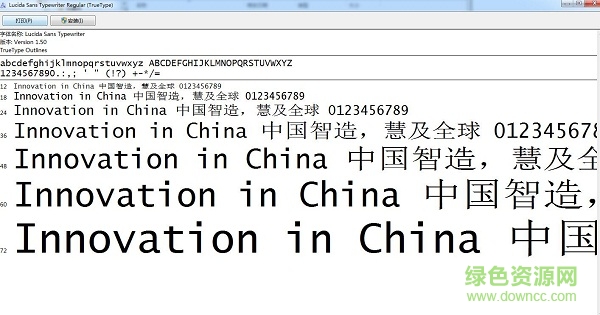
lucida sans typewriter字體是一款擁有高辨識(shí)性的經(jīng)典等寬字體,字型干凈大氣,易讀性出色,就像是打字機(jī)打出來(lái)的字體一樣,可用于網(wǎng)頁(yè)設(shè)計(jì)或編程設(shè)計(jì),歡迎大家免費(fèi)下載!
【Courier】
是一個(gè)等寬字體的粗襯線字體,主要是依據(jù)打字機(jī)所打印出來(lái)的字形來(lái)設(shè)計(jì),于1955年由Howard “bud” Kettler設(shè)計(jì)完成。在現(xiàn)今的電子時(shí)代,此字體也常被使用,因?yàn)槠涞葘挼奶匦钥梢暂p易地對(duì)齊字段的左右邊界,也成為腳本和程式設(shè)計(jì)中源代碼的常用字體!
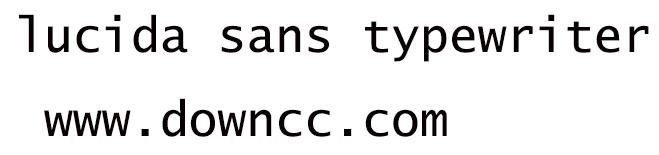
【Consolas】
Consolas是一套固定字符寬度的字型,屬無(wú)襯線字體,由 Lucas de Groot 設(shè)計(jì)。這套字型使用了微軟的 ClearType 字型平滑技術(shù),
【Andale Mono】
是Monotype公司出品的一個(gè)等寬字體風(fēng)格的無(wú)襯線字體,其特色在于字符有高度的可辨識(shí)性,例如數(shù)字“0“中有一點(diǎn),可輕易與大寫(xiě)字母“O“區(qū)別;容易混淆的數(shù)字”1“、小寫(xiě)字母”l“和大寫(xiě)字母”I“也加入襯線設(shè)計(jì)以利分辨。